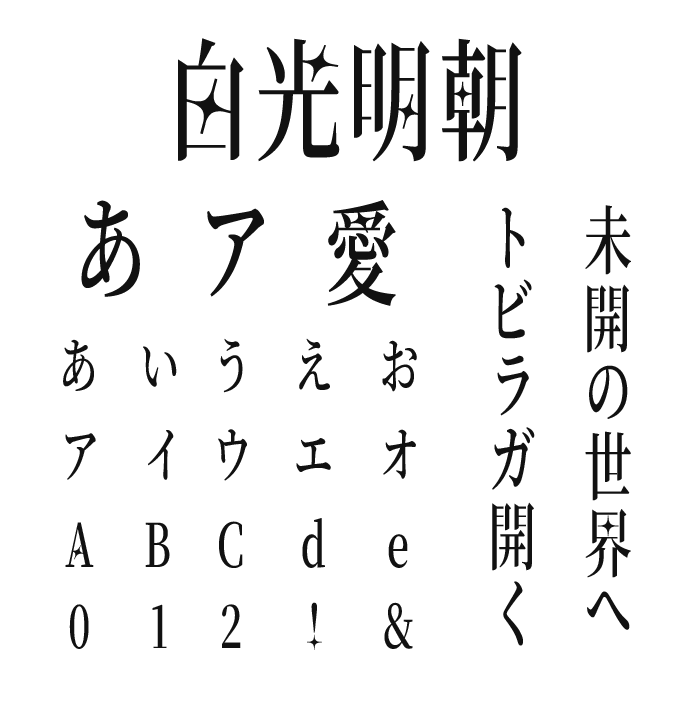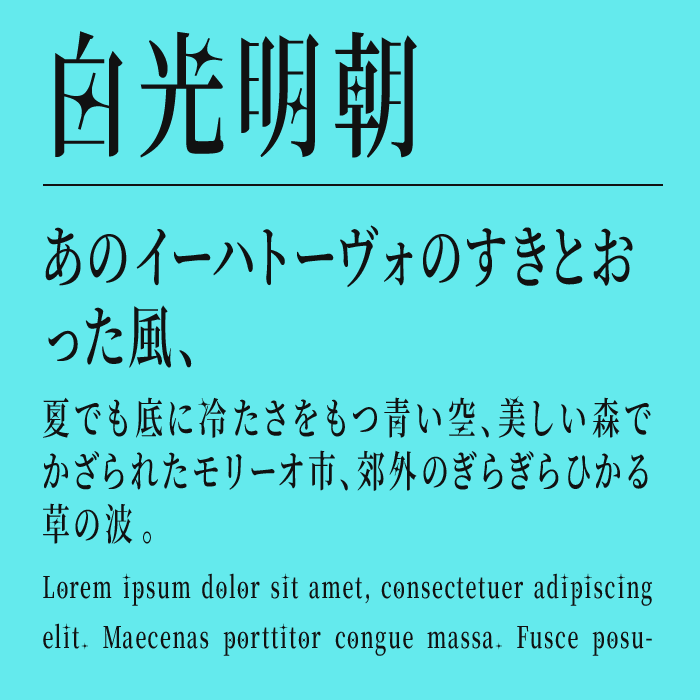
白光明朝は、細く鋭い線と、縦方向にすっと伸びた文字の形と、文字によって星が散りばめられてたキレイな明朝系フォントです。
横線はかなり細く、縦線との強弱がはっきりしているため、一般的な明朝体よりもシャープで緊張感のある表情に見えます。漢字のハネや払いも鋭く、見出しにすると文字の輪郭がきれいに浮かび上がります。
一方で、ひらがなには筆文字のような柔らかな流れが残されており、硬質な漢字との組み合わせにも面白さがあります。和風のタイトルや書籍、映画、ファッション、ブランドビジュアルなど、落ち着いた中にも少し非日常的な雰囲気を出したい場面に合いそうです。文字数を絞って余白を広めに取ると、このフォントの細さや美しい線をより楽しめます。
収録文字は、漢字・ひらがな・カタカナ・アルファベット・数字・記号が収録。